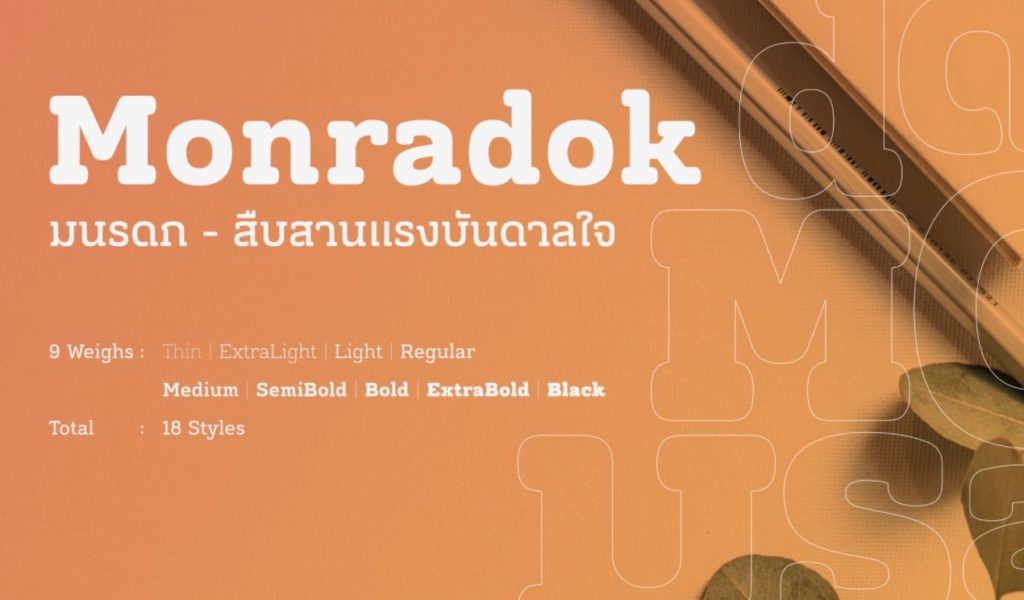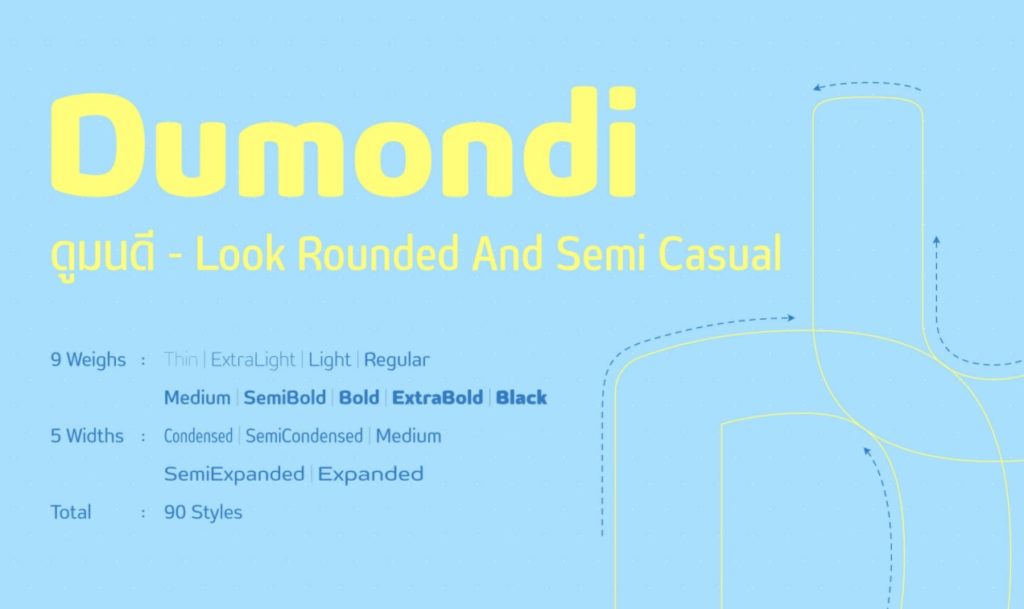
สำหรับใครที่อยากจะหาฟอนต์ไทยสวย ๆ ดูสบายตามาใช้งาน ทีมงานมีฟอนต์จาก Jipatype ทั้งหมด 8 ฟอนต์มาแนะนำให้ชมกันค่ะ
รวม 8 ฟอนต์ไทย สบายตา ใช้ตกแต่งงานกราฟิกสวย ๆ จาก Jipatype
1. อบอุ่นใหม่ (Opun Mai)
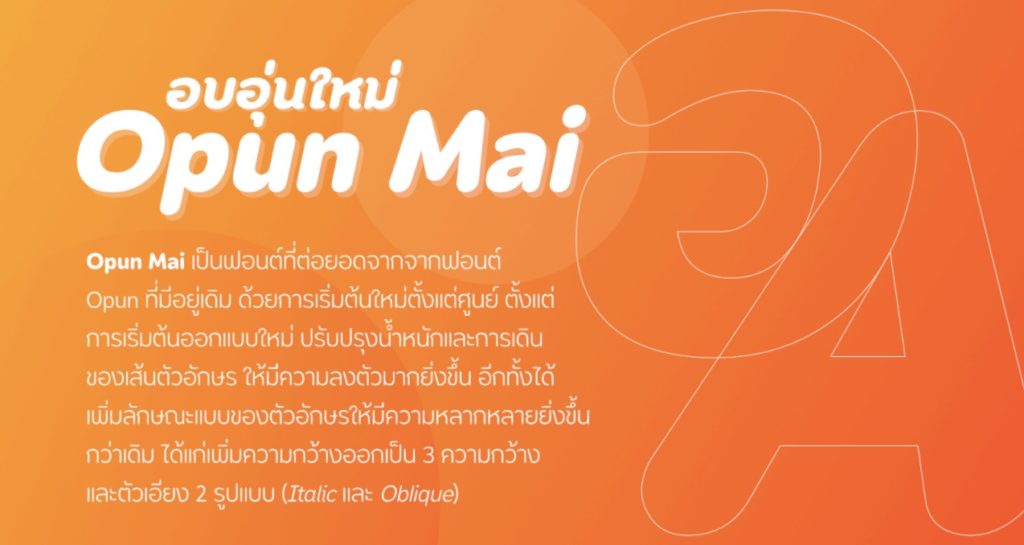
2. มณีษร (Manison)
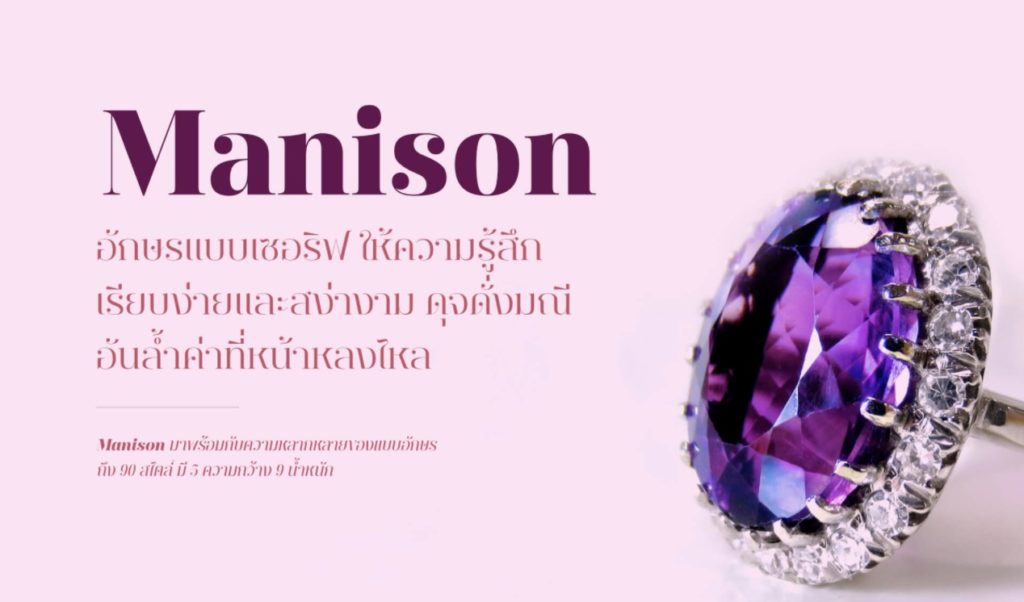
3. บริบูรณ์ (Boriboon Font)
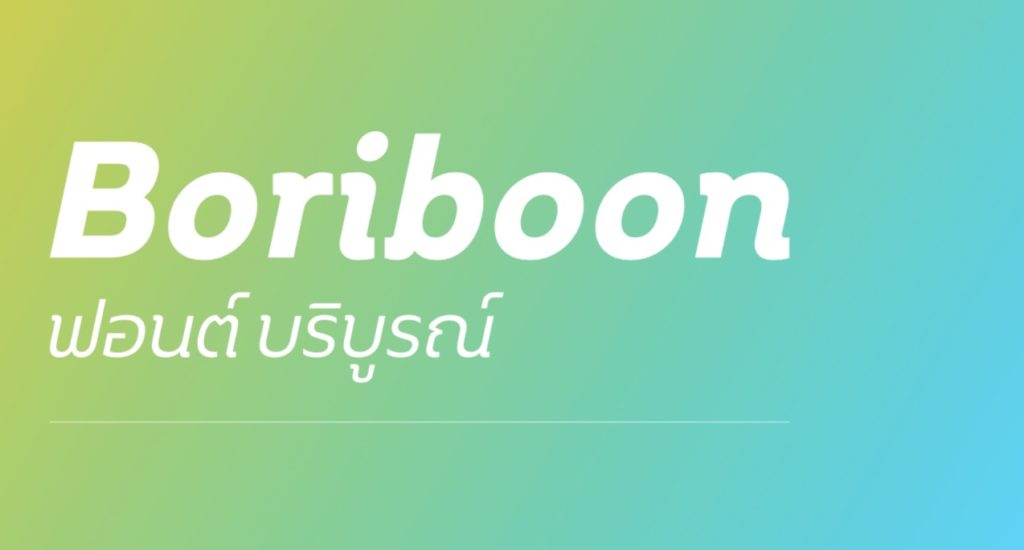
4. อนันตษร (Anantason Font)
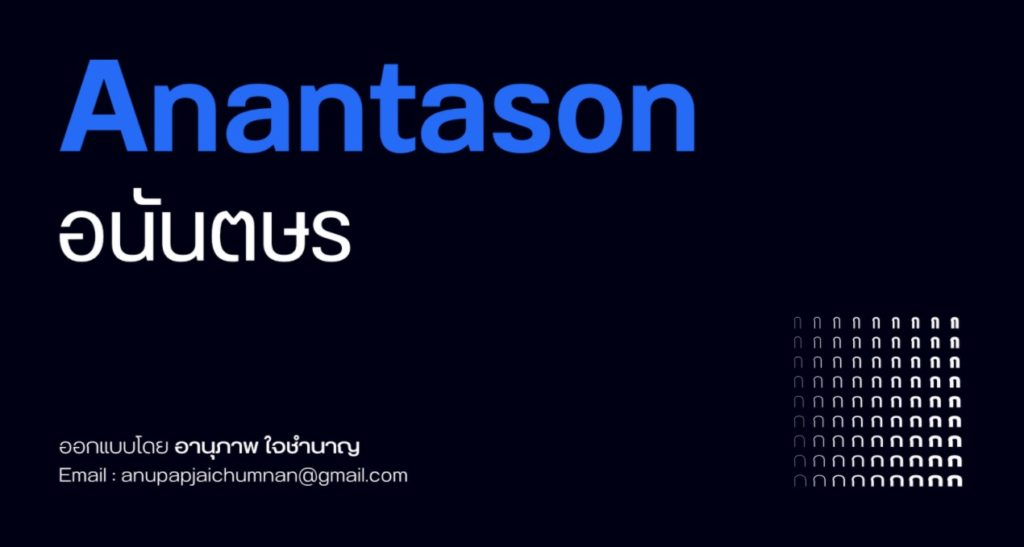
5. เพชรละมุน (Petchlamoon)
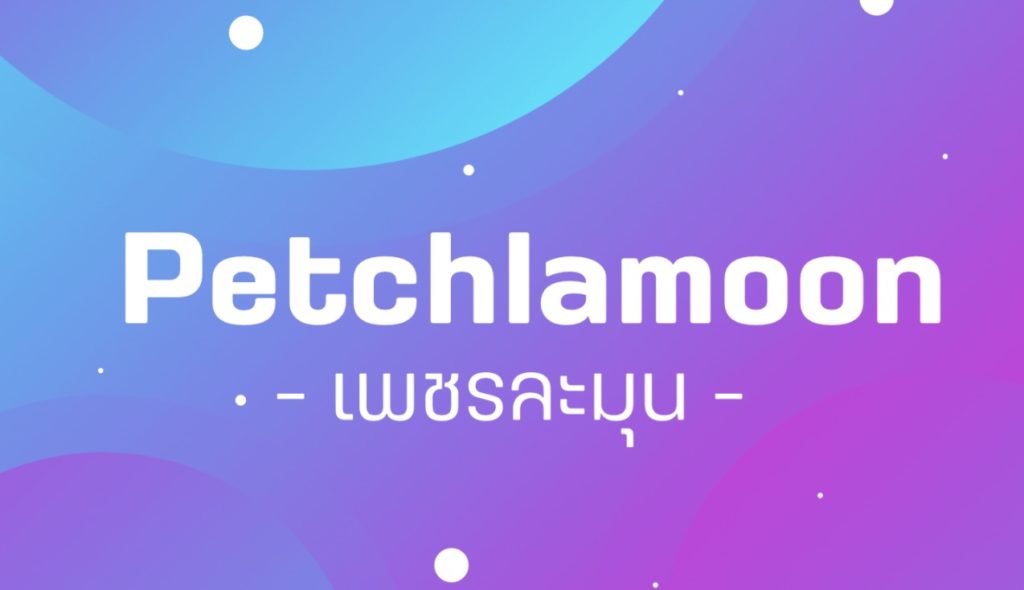
6. ดูมนดี (Dumondi)
7. มนต์นภา (Montnapha)
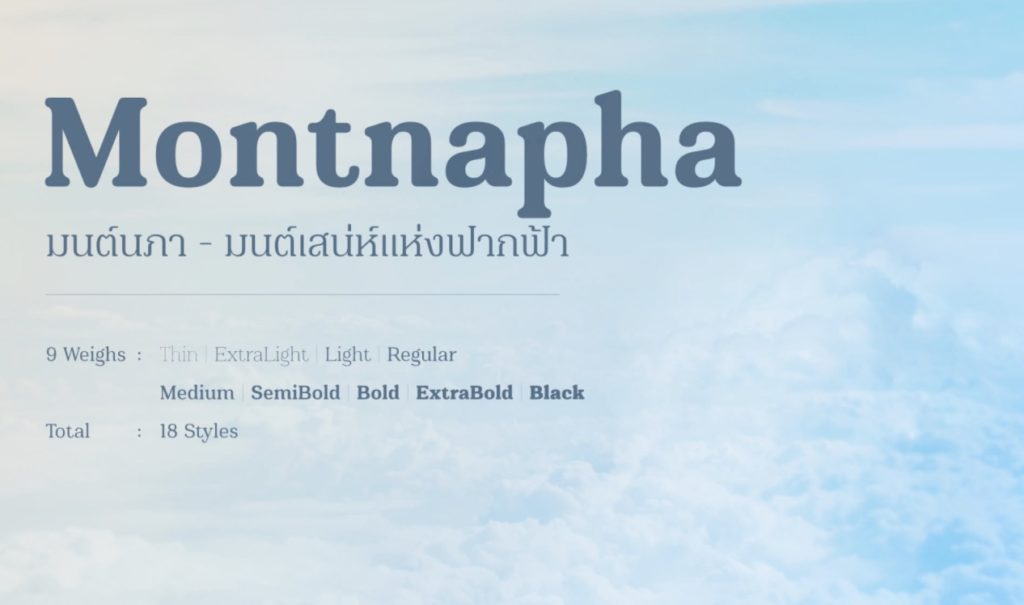
8. มนรดก (Monradok)